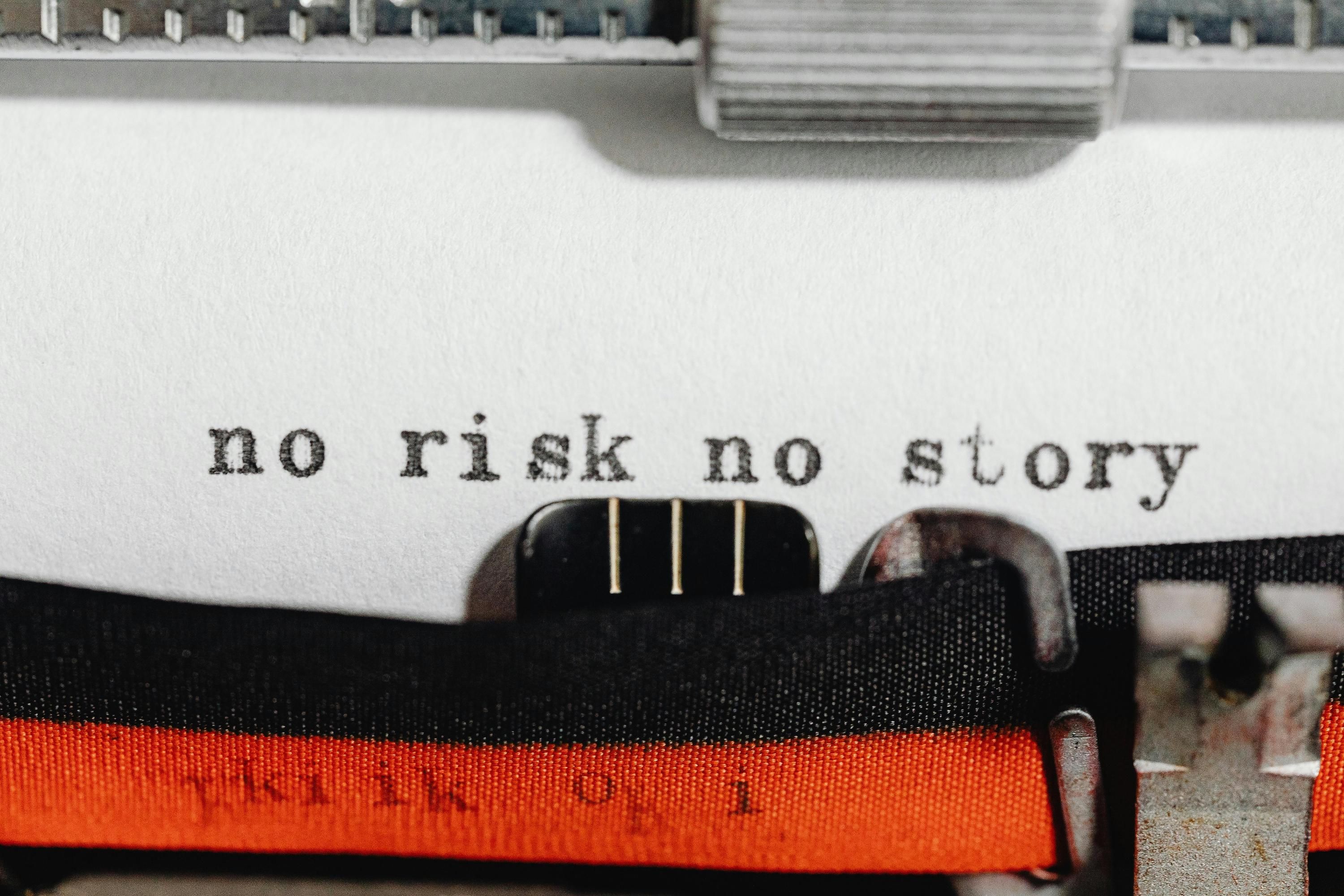
Чому всі сценарії пишуться одним шрифтом?
Всі сценарії у світі пишуться шрифтом Courier 14. Його обрали для цієї справи не випадково. Основна ознака, яка зробила його стандартом – він моноширний.
Що таке моноширний шрифт
Це вид шрифту, у якому кожна літера займає однакову кількість простору на аркуші.
У сценаристів є негласне правило: одна сторінка – це одна хвилина екранного часу. наприклад, якщо сценарій займає 40 сторінок, то це 40 хвилин екранного часу. Звісно, ці цифри приблизні та дуже орієнтовні.
Водночас виникає питання: чи можна використовувати будь-який моноширний шрифт? Однозначно сказати так чи ні складно. Наприклад, авторка відео відзначає, що навіть якщо шрифт не був прописаний умовами якогось конкурсу сценарії, то навряд чи ті тексти, які написані іншими моноширними шрифтами, візьмуть до рук.
За її словами, це справа системності та того, що до цього всі звикли, а в кінематографі не дуже люблять зміни.